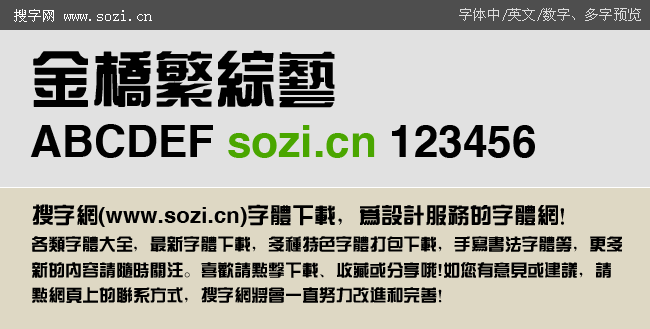
金橋繁綜藝
搜字網(wǎng)提供一款金橋繁綜藝下載。此款字體為繁體字體,綜藝體是黑體的一種變體,也是藝術(shù)字的一種。特點(diǎn)是筆劃更粗,盡量將空間充滿。同時(shí)為了美觀,對拐彎處的處理較為圓潤。適用于廣告、報(bào)刊等的標(biāo)題及海報(bào)展板等設(shè)計(jì)場合使用。